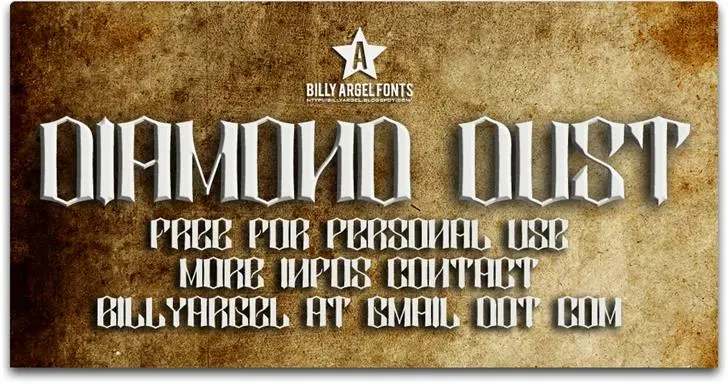
Aqui está uma descrição para a página de download da fonte ‘DIAMOND DUST Font’, categoria Gothic Fonts: Na família de letras gothicas, a DIAMOND DUST se destaca pela sua textura única e elegante. Inspirada na atmosfera cinzenta do sol nascente ou no topo de uma montanha afar, essa fonte oferece um tom ponderoso que reflete sua estrutura firme. Sua tipografia é perfeita para criar um ambiente criativo e sofisticado em projetos digitais. Criada pelo designer Hamilton, a DIAMOND DUST não apenas traz uma experiência visual única, mas também se destaca por seu uso eficaz na criação de títulos impactantes ou textos detalhados. Suas linhas são levemente desbotadas e suas formas delicadamente arredondadas criam um contraste interessante que torna a DIAMOND DUST uma opção de fontes icônicas para qualquer projeto. Agora, com a disponibilização da DIAMOND DUST, designers poderão explorar novas maneiras de moldar seus projetos digitais com este design elegante e sofisticado. Este é um recurso gráfico ideal para criar uma identidade visual única, seja em logotipos, materiais publicitários ou até mesmo sites web, garantindo que sua mensagem tenha o impacto desejado no público alvo.